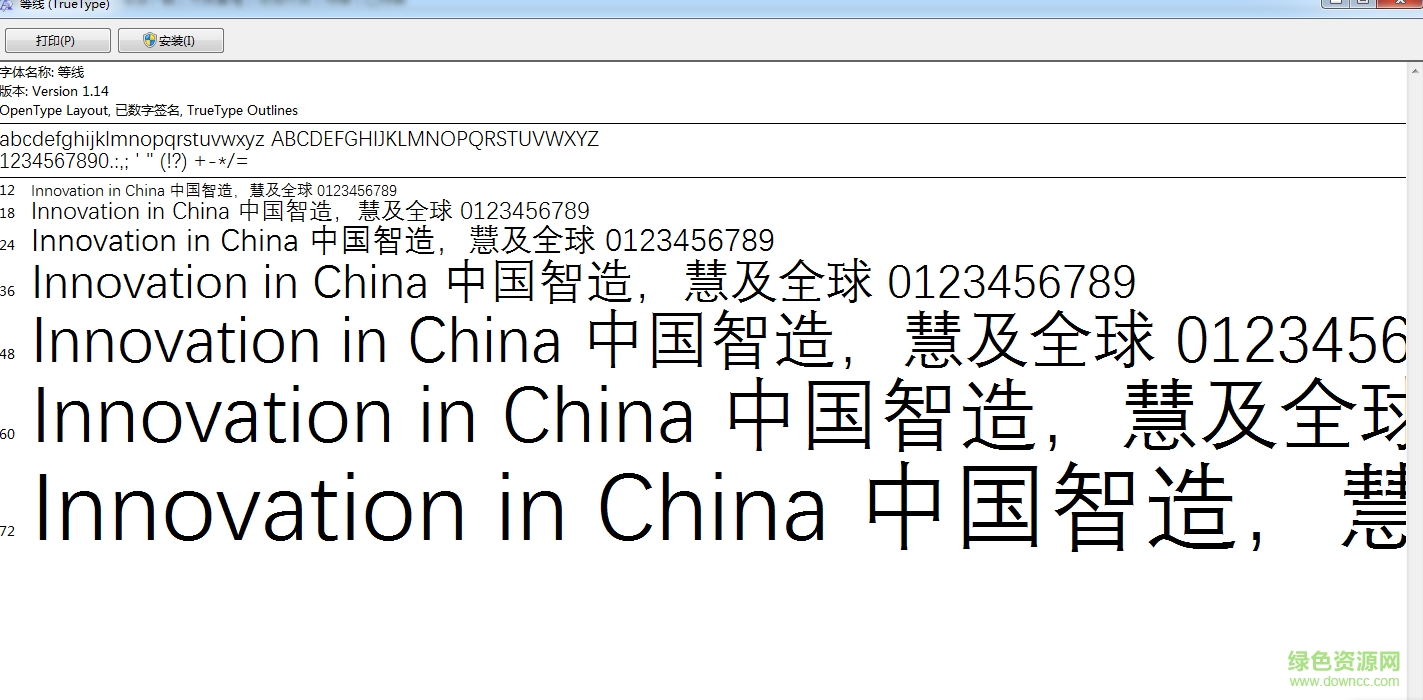
等線regular字體
dengxian regular字體又稱等線regular字體,常用做中文正文字體,每個字的線條粗細都一樣,字形莊重樸素毫無裝飾,機械感十足,有需要者歡迎在綠色資源網(wǎng)下載!
等線體介紹
等線體是微軟公司windows 8 的標準默認經(jīng)典字體。包括格洛退斯克和埃及體。它們的特點是都有幾乎相等的線條,前者好像漢字中的黑體,完全拋棄了字腳,只剩下字母的骨骼,顯得樸素端正,十分清晰,但過于平板,因此也叫做無字腳體。